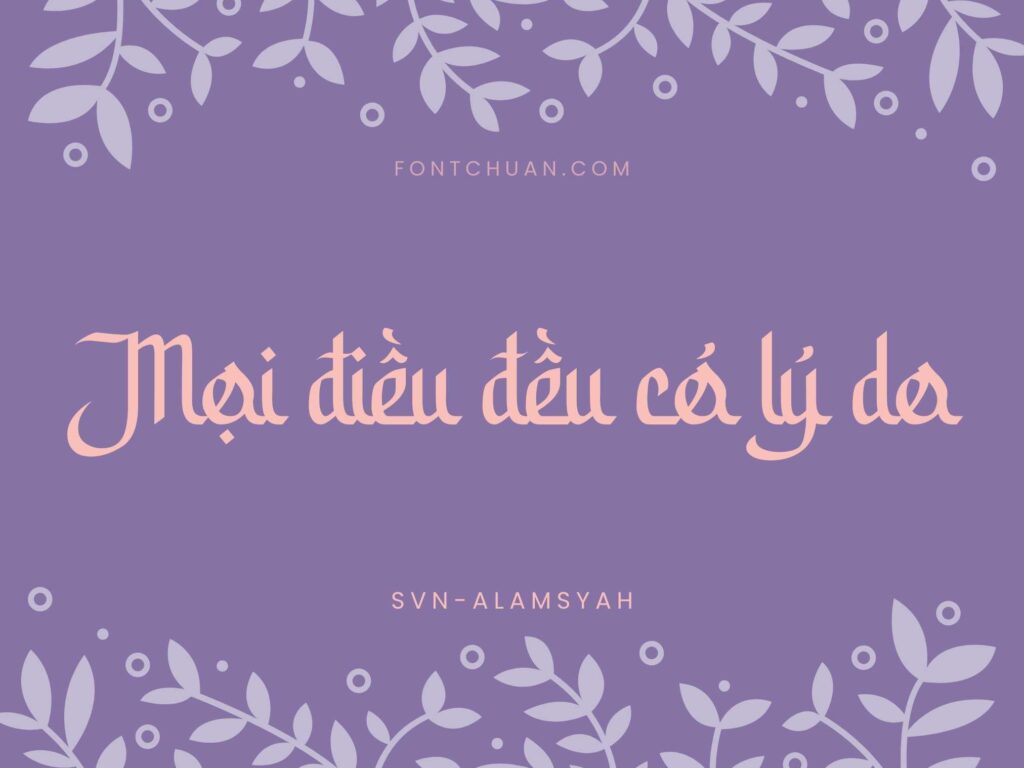
Font SVN Alamsyah Việt Hóa
Tác giả Font: Kong Font
Alamsyah là một font chữ độc đáo được thiết kế bởi Kong Font, mang phong cách hiện đại với đường nét mềm mại và uyển chuyển. Font này mang đến sự sang trọng và cá tính, phù hợp cho nhiều mục đích sử dụng như thiết kế logo, tiêu đề, ấn phẩm quảng cáo, thời trang và bao bì sản phẩm. Với hơn 200 ký tự hỗ trợ đa ngôn ngữ, Alamsyah là một lựa chọn tuyệt vời cho các nhà thiết kế muốn tạo ra những tác phẩm chuyên nghiệp và sáng tạo. Font đã được Việt hóa để hỗ trợ tiếng Việt bởi Styleno.1 Fonts, đồng thời hỗ trợ nhiều ngôn ngữ khác, giúp mở rộng phạm vi sử dụng trên toàn cầu. Font này được thành viên của Font Chuẩn sưu tầm và chia sẻ, đáp ứng nhu cầu của bạn đọc và ứng dụng thực tế vào các dự án thiết kế.
Đặc điểm thiết kế của Alamsyah bao gồm cấu trúc chữ cân đối, đường nét mềm mại nhưng vẫn giữ được sự mạnh mẽ và thu hút. Font này phù hợp cho các ứng dụng như thiết kế logo, nhãn hiệu, bao bì sản phẩm, tiêu đề sách và áp phích. Các ngành nghề phù hợp bao gồm quảng cáo, thương hiệu, thời trang và thiết kế sáng tạo.